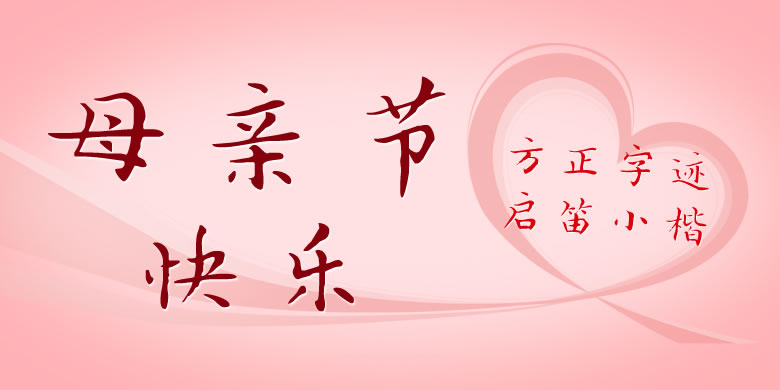
方正字迹-启笛小楷
方正字迹-启笛小楷,这款字体结构工整、笔画清晰,兼顾美观与易读性,适用于标题、正文、海报、包装、LOGO 等多种场景。字形优雅稳定,风格百搭耐看,适配日常排版与创意设计,让文字呈现更舒适、更具质感。方正字迹-启笛小楷一笔一画,皆是细节,以均衡的比例、流畅的线条打造舒适视觉体验,字形端正大气,风格简约现代。无论是商业设计、品牌宣传还是日常排版,都能轻松驾驭,让文字更有格调与力量。方正字迹-启笛小楷字体下载。
方正字迹-启笛小楷由书法家启笛先生创作。这款字体遥接魏晋之风,结构宽绰,骨力挺劲,结构谨严,反映了书法家恬淡自然的艺术追求。启笛小楷的风格古雅本真,适用于文化类的宣传设计,以及商业类品牌的广告和产品包装设计。